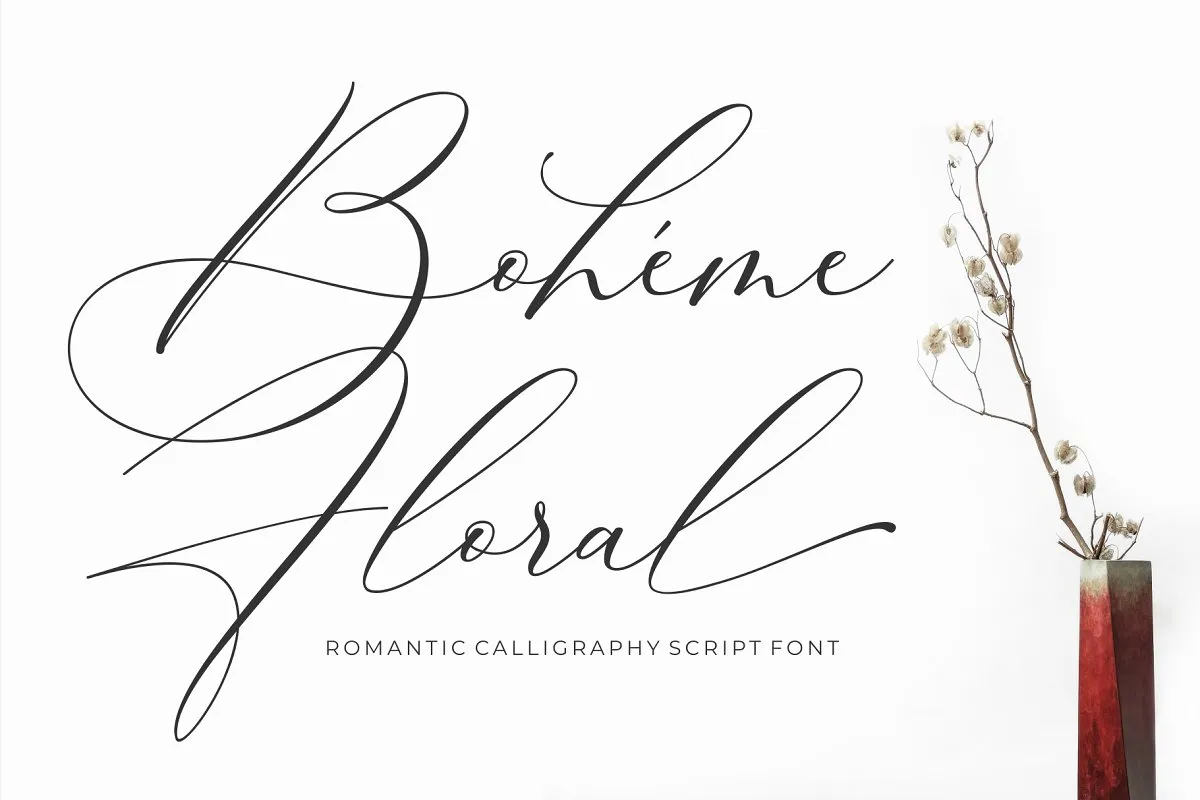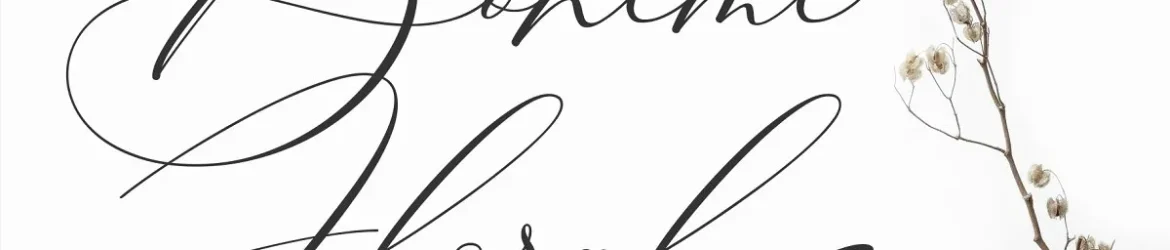
Descubra a encantadora Boheme Floral Script Font, ideal para criar designs envolventes e delicados. Introduzida pelo designer 50Fox, esta elegante fonte de escrita floral é perfeita para um novo dia cheio de romantismo. Bohéme Floral oferece uma dose de sofisticação clássica da escrita romântica, acompanhada por ligações fofas, letras alternativas e detalhes florais que o tornam único. Esta font é perfeitamente indicada para um vasto espectro de aplicativos. Use-a em logotipos, citações impressas, insígnias, embalagens, headlines, cartazes, camisetas ou materiais de vestuário, cartões de agradecimento e até mesmo convites de casamento. Bohéme Floral Script Font é uma escolha perfeita para qualquer projeto que você deseja tornar mais elegante e delicado, criando um toque romântico em cada design.